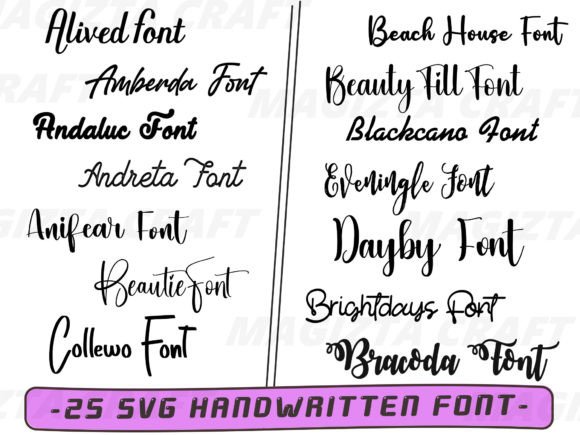
Neat & Clean Handwritten Font Bundle V.1
Если вы ищете высококачественные ресурсы, такие как Neat & Clean Handwritten Font Bundle V.1, этот премиум-пакет — фантастический выбор для ваших творческих проектов.
Создаете ли вы продукты POD (печать по требованию), свадебные приглашения или графику для социальных сетей, Neat & Clean Handwritten Font Bundle V.1 станет идеальным выбором.